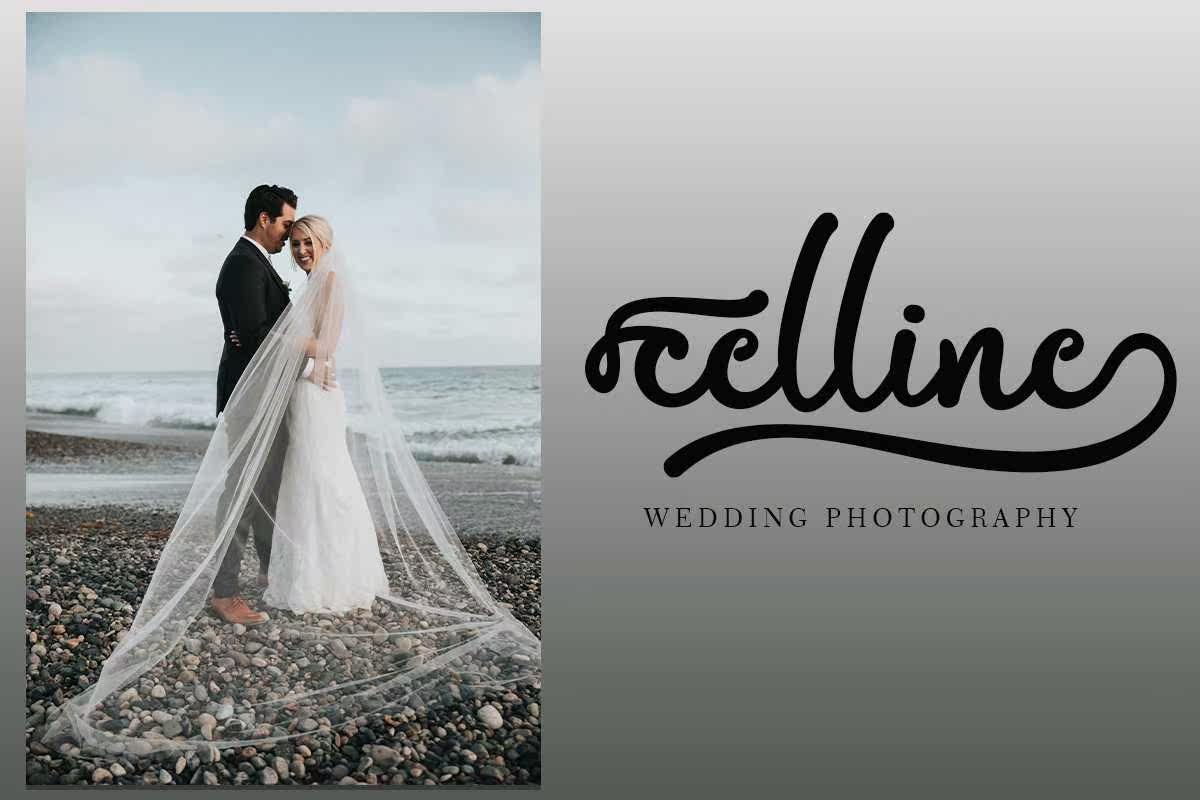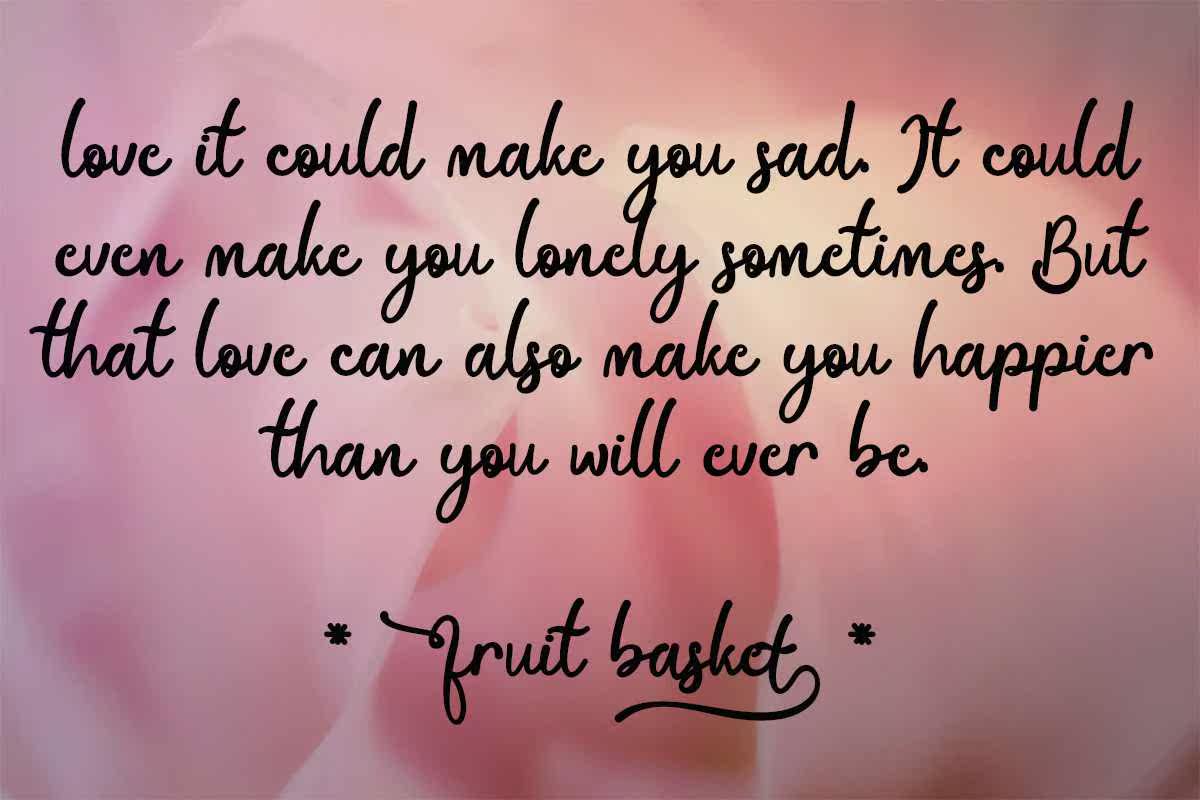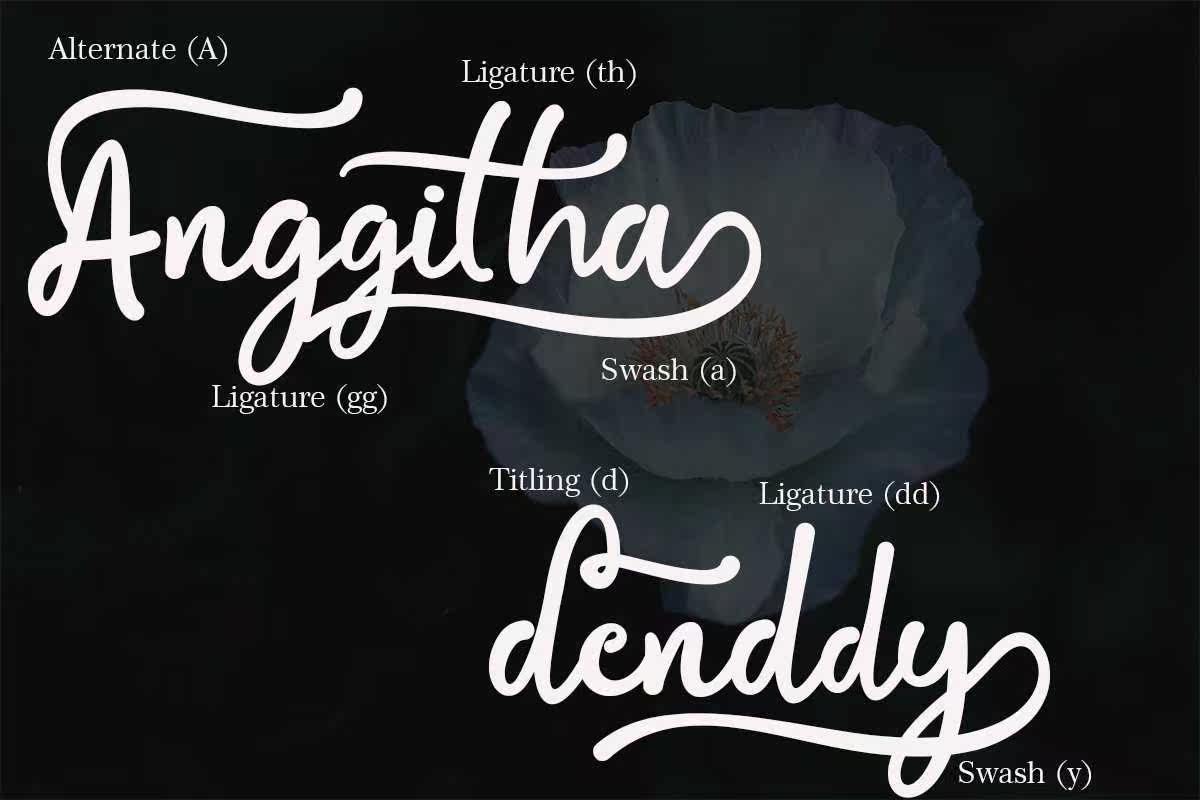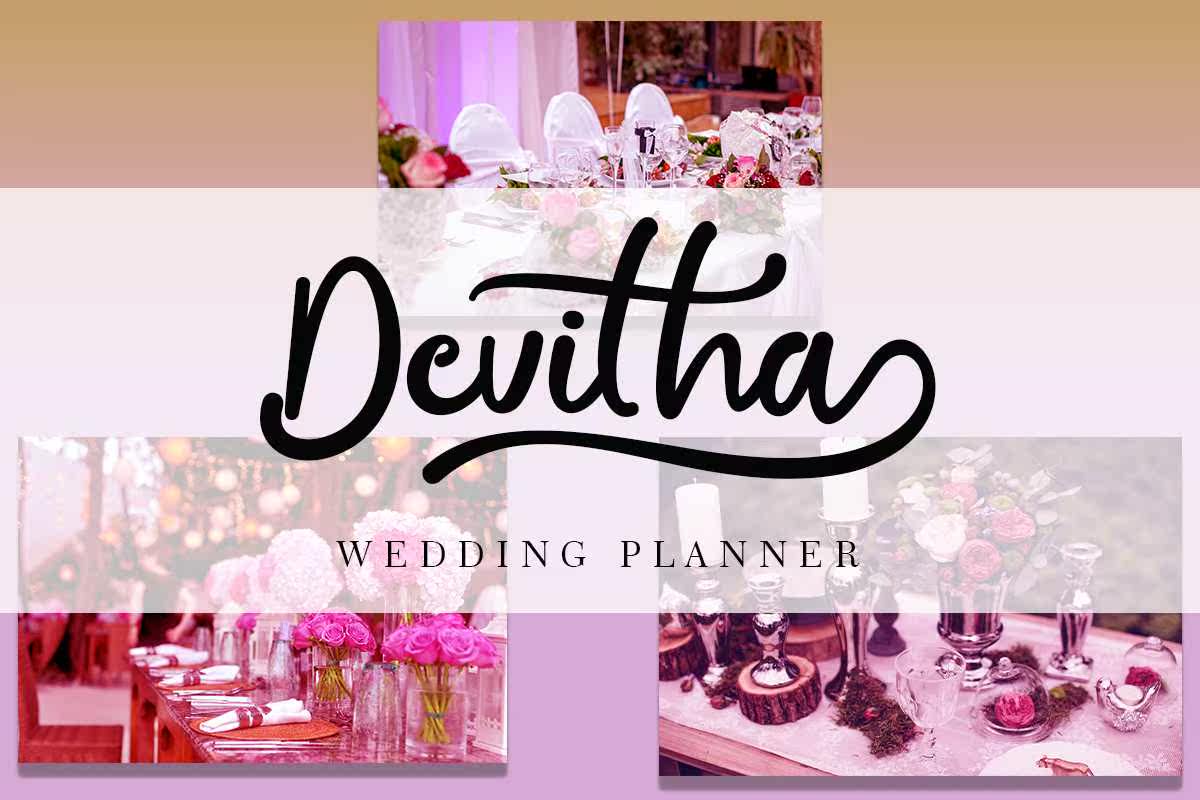
BIALLETTA是一种现代化的书写字体。这种字体非常漂亮和美观。除了美观和美观之外,这种字体还非常独特,可以提高您的工作质量。这种字体适用于所有类型的工作。它适用于婚礼设计、品牌推广、邀请、签名、标签、徽标、捕获您在社交媒体上的美丽时刻、您的商业宣传,还有更多。BIALLETTA是现代的书写字体。这种字体非常漂亮和美观。除了美观和美观之外,这种字体还可以让您的作品质量大大提高。这种字体适用于所有类型的作品。它适用于婚礼设计、品牌推广、邀请函、签名、标签、徽标、捕捉您在社交媒体上的精彩瞬间、商业宣传等。